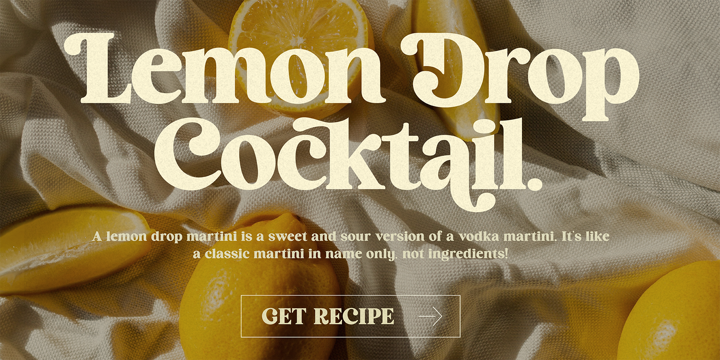
Myfonts HV Cocktail Font 2021
[Myfonts] HV Cocktail Font (2021)
Cocktail - элегантный ретро-засечки с художественным оттенком.
Специально разработан для винтажных, ретро, элегантных проектов, прекрасно подходит для создания простых, жизненных дизайнов, таких как логотипы, заголовки, упаковки и многое другое.